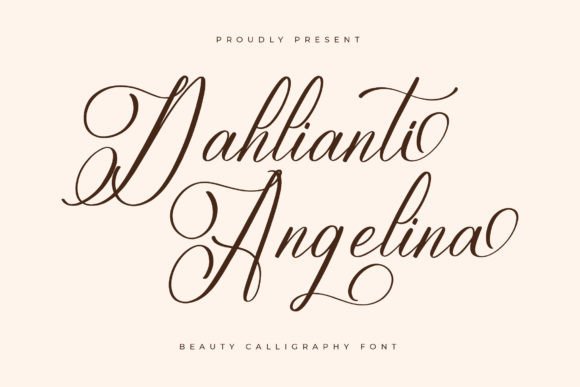
Dahlianti Angelina
適切なデザイン要素を見つけるのは難しい場合がありますが、Dahlianti Angelinaは作品を即座に引き立てる優れたコレクションを提供します。
POD(オンデマンド印刷)製品、結婚式の招待状、またはソーシャルメディアのグラフィックを作成している場合でも、Dahlianti Angelinaは理想的です。